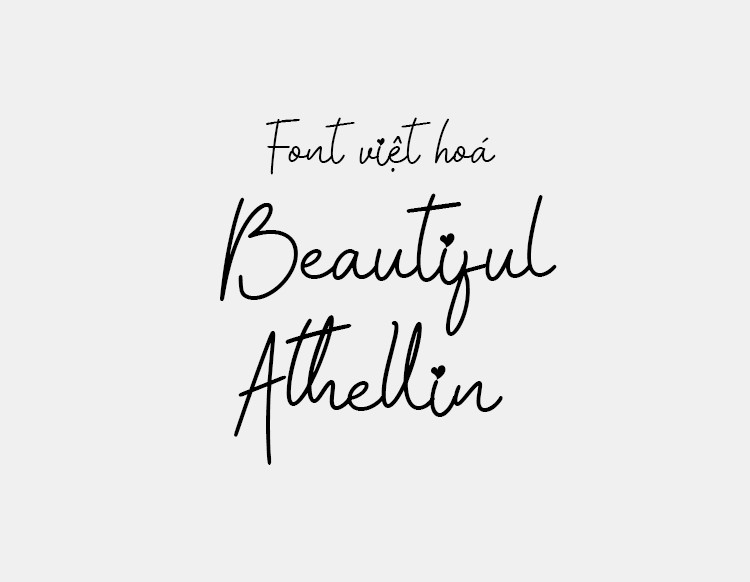
Giới thiệu về Font việt hoá MJ Beautiful Athellin
Trong thế giới đồ họa hiện đại, việc lựa chọn một Font Chữ phù hợp đóng vai trò quan trọng trong việc truyền tải cảm xúc của tác phẩm. Font việt hoá MJ Beautiful Athellin là một bộ font chữ mang phong cách script hiện đại, kết hợp giữa sự mềm mại của nét bút thủ công và tính chuyên nghiệp trong cấu trúc chữ. Đây là lựa chọn lý tưởng cho những ai đang tìm kiếm sự thanh lịch và tinh tế cho các dự án cá nhân hoặc giáo dục.
Đặc điểm nổi bật của bộ font
Bộ font này nổi bật với các đường nét thanh mảnh, bay bổng nhưng vẫn giữ được độ dày vừa phải để đảm bảo tính dễ đọc trên nhiều nền tảng khác nhau. Khi sử dụng Font việt hoá MJ Beautiful Athellin, người dùng có thể dễ dàng tạo ra các sản phẩm như thiệp mời, bìa sách hoặc các bài giảng điện tử sinh động. Sự tương thích hoàn hảo với bảng mã Unicode giúp quá trình gõ tiếng Việt trở nên mượt mà, không bị lỗi font hay mất dấu.
Ứng dụng thực tế của Font việt hoá MJ Beautiful Athellin
Đối với học sinh và giáo viên, bộ font này hỗ trợ đắc lực trong việc trang trí bảng tin, làm báo tường hoặc thiết kế các slide thuyết trình ấn tượng. Tính nghệ thuật cao của MJ Beautiful Athellin giúp khơi gợi cảm hứng sáng tạo và làm cho nội dung truyền tải trở nên gần gũi hơn. Ngoài ra, các nhà thiết kế tự do cũng thường xuyên sử dụng nó cho logo và nhận diện thương hiệu nhờ vẻ đẹp vượt thời gian.
Lưu ý khi sử dụng
Để phát huy tối đa vẻ đẹp của font, bạn nên kết hợp với các font chữ không chân (sans-serif) đơn giản để tạo sự cân bằng. Việc điều chỉnh khoảng cách dòng và kích thước chữ cũng rất quan trọng để đảm bảo tính thẩm mỹ cao nhất.